Highlights der Set Sail Studios Foundry.
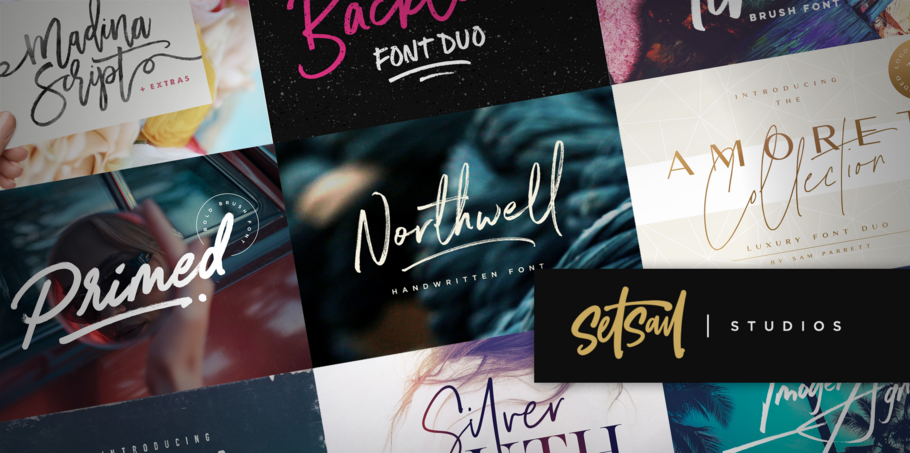
Set Sail Studios.
Set Sail Studios ist eine Einmann-Foundry und wird von Sam Parrett in seinem Home Office in Bristol, Großbritannien, betrieben. Er startete seine Karriere als freiberuflicher Grafik-Designer in der Musikbranche. Irgendwann suchte er sich jedoch eine neue Herausforderung. Er folgte seiner wachsenden Leidenschaft für Schriften und Typografie und brachte 2014 seine erste Schriftart heraus. Dabei war es sein Ziel, die Design-Welt mit einer Palette auffallender, einzigartiger Schriftarten durchzuschütteln, die sich so ganz und gar von den herkömmlichen Buchstabenformen unterschieden. Er hat sich auf handgezeichnete Schrift-Designs spezialisiert. Seine luxuriösen Zeichensätze werden häufig für Lifestyle-Marken verwendet, während seine Pinsel- und Markerschriften oft die perfekte Lösung für Designprojekte im Retrostil oder mit rustikalem Einfluss bieten.
Northwell
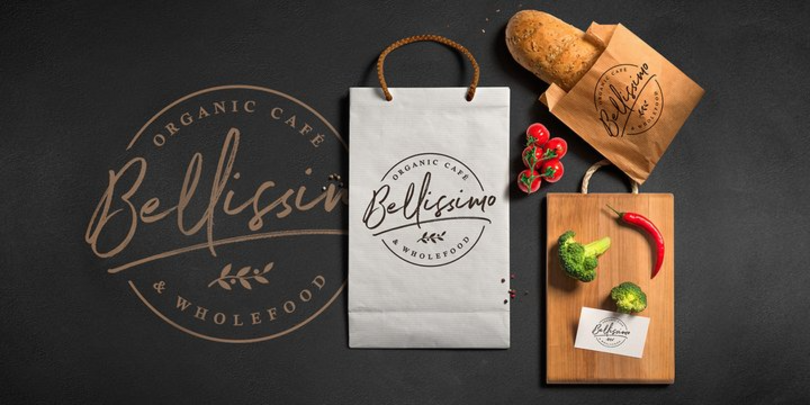
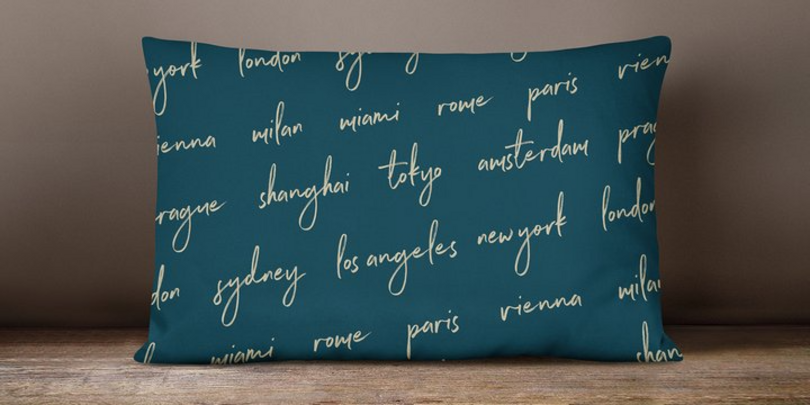
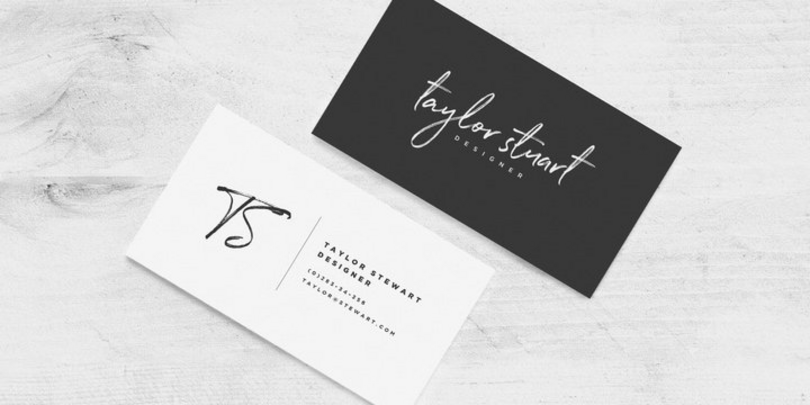
Northwell eine rustikale, elegante handschriftliche anmutende Schriftart mit einem persönlichen Charme, ist mit seinen schnellen trockenen Strichen und seinem Signaturstil eine ideale Lösung für Branding-Projekte, Homeware-Designs oder Produktverpackungen. Die Northwell-Schriftfamilie umfasst eine rustikale, texturierte Version und einen sauberen, polierten Stil. Die saubere Version weist keine raue Pinseltextur auf. Diese wird durch vollständig glatte Ränder ersetzt, die sich optimal für Spezialdrucke eignen oder einfach dem Design einen eleganten Touch verleihen. Viele Consumer-Marken haben Northwell bereits für ihre Marketing-Materialien verwendet, unter anderem Ralph Lauren und die Londoner Café-Kette EL&N. Northwell liefert einen eleganten aber trotzdem persönlichen Touch für die gesamte Marke eines Unternehmens. Sie ergänzt den Stil einer Marke überall dort, wo sie erscheint.
Primed
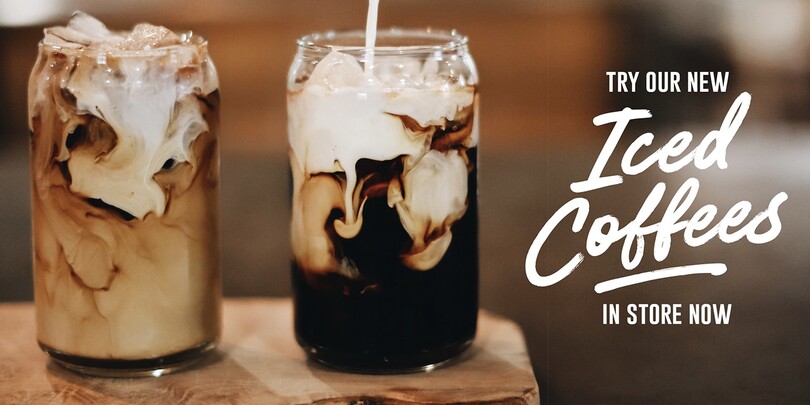
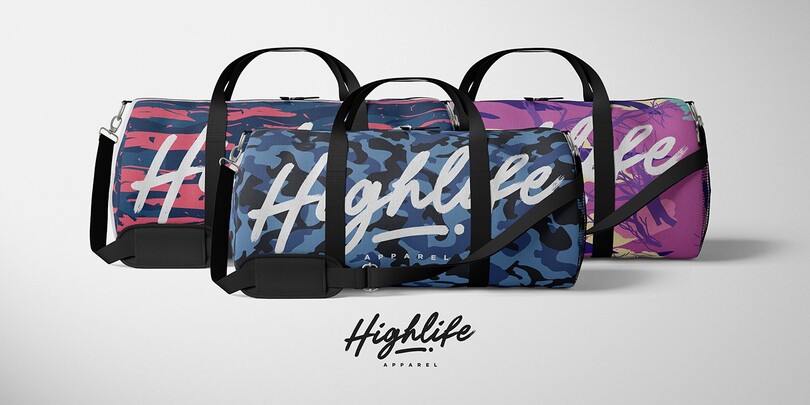
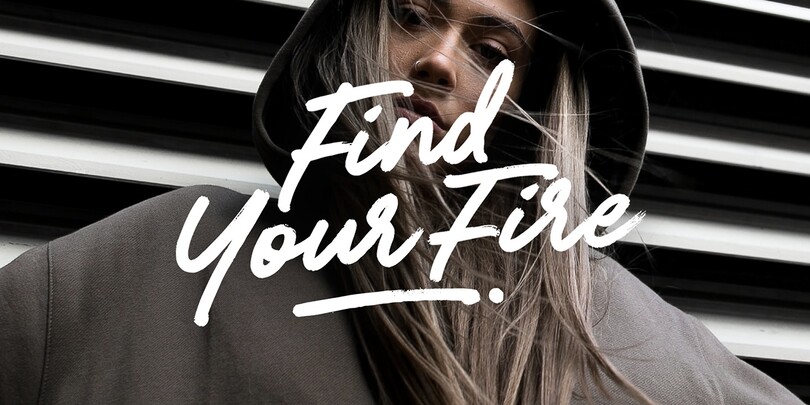
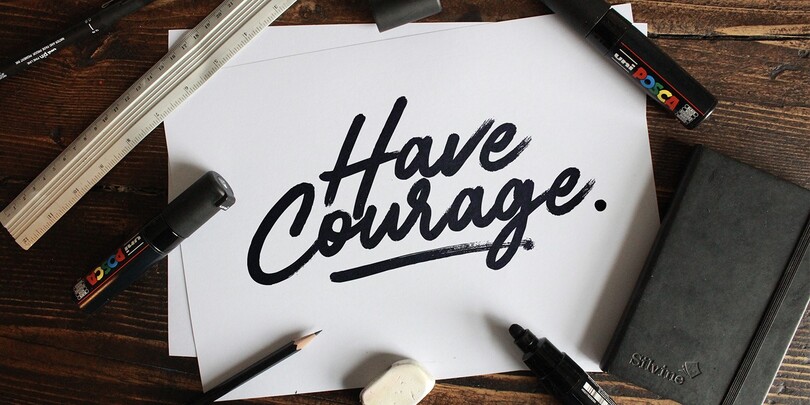
Präsent, plakativ und für den bleibenden Eindruck gedacht. Primed ist eine authentische, handgezeichnete Pinselschriftart, die mit richtigen Markern entwickelt wurde. Perfekt für unübersehbare Display-Texte, Logos, handschriftliche Zitate, Produktverpackungen und vieles mehr! Primed umfasst neben einem vollständigen alternativen Satz Groß- und Kleinbuchstaben auch einen Satz von 18 Schwungbuchstaben, die sich hervorragend für die Untermalung von Buchstaben und einen Hauch von zusätzlichem individuellem Stil eignen. Die alternativen Buchstaben und die Schwungbuchstaben sind als eigenständige Schriftarten enthalten. Primed umfasst außerdem 47 Ligaturen. Diese Doppel- und Dreifachbuchstabenkombinationen tragen zu einem natürlicheren Verbindungs- und Flusseffekt bei.
Silver South
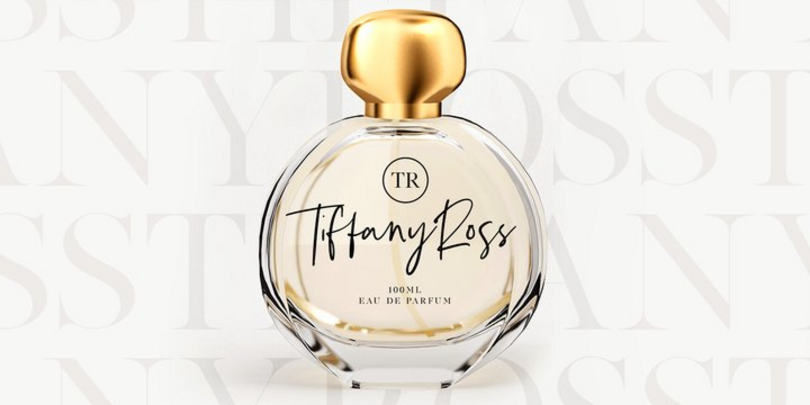
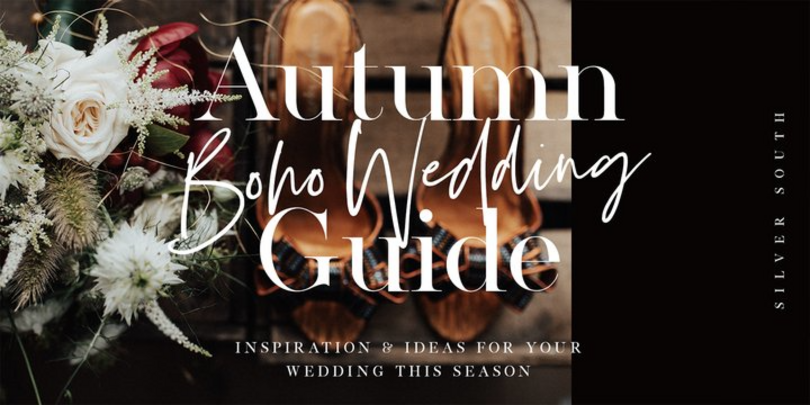
Die Silver South Font Duo ist eine klassische moderne Paarung aus Script- und Serif-Schriftarten. Hier wurden eine elegante Didot-Serif-Schriftart und eine frei fließende expressive Schriftvariante kombiniert, um eine wunderschöne typografische Harmonie für eine große Vielfalt an Design-Projekten zu erzeugen. Dazu gehören Logos und Branding, Lifestyle-Marken, Social Media-Beiträge, Werbeanzeigen und Produkt-Designs. Die Silver South Script umfasst auch 38 Zeichenligaturen und ermöglicht damit einen natürlicheren, stärker handschriftlich geprägten Textcharakter.
Faith and Glory
Faith and Glory: zwei handgezeichnete Pinselschriftarten die perfekt aufeinander abgestimmt sind, um eine wunderschöne, rustikale Typografie mit einem persönlichen Touch zu schaffen. Das Duo eignet sich hervorragend für Logos, gedruckte Zitate, Einladungen, Bild-Overlays, Grußkarten, Produktverpackungen, Textüberschriften usw. Faith and Glory One ist eine Schriftart mit Groß- und Kleinbuchstaben, Satzzeichen, Zahlen, verschiedenen Kleinbuchstabenalternativen und mehrsprachiger Unterstützung. Faith and Glory Two ist eine komprimierte Pinselschriftart, die ausschließlich aus Großbuchstaben besteht. Außerdem umfasst sie Satzzeichen, Zahlen, Alternativen für Zahlenzeichen und mehrsprachige Unterstützung.
Madina Script
Die Madina Script ist eine lebenslustige, aber gleichzeitig elegante Schriftart voller Energie. Designer können damit im Handumdrehen wunderschöne handschriftlich anmutende Typografien erstellen. Die Madina Script mit ihren stark betonten Kurven und Schleifen lässt jeden Text hervorstechen. Sie eignet sich hervorragend für Logos, gedruckte Zitate, Einladungen, Karten, Produktverpackungen und Überschriften. Die Madina Script umfasst einen vollständigen Satz von Kleinbuchstabenvarianten für mehr Authentizität und eine Bonus-Schmuckschrift für einzigartige und elegante finalisierende Touches für Skripttext. Die Schriftart bietet zwei alternative Stile: eine grobe, texturierte Pinselversion für einen rustikalen, handschriftliche Stil und eine saubere, glatte Version für ein seidenartiges Finish.
Backlash
Mit einer ausgefallenen Schriftart und einer Variante mit Kleinbuchstaben eignet sich dieses leidenschaftliche Paar handgezeichneter Markerschriftarten optimal für die Gestaltung handschriftlicher Zitate, Branding- und Logoprojekte, Merchandising, Social Media-Beiträge und Produktverpackungen. Die Backlash Font Duo beinhaltet Backlash Script, eine handgezeichnete Schriftart mit Klein- und Großbuchstaben. Sie beinhaltet außerdem Backlash Small Caps, eine handgezeichnete Sans-Schriftart mit zwei Sätzen an Großbuchstaben (ausschließlich). Beide enthalten Zahlen und Satzzeichen. Die Schriftart umfasst jedoch zusätzlich Ligaturen (Doppelbuchstaben) für „ll“, „tt“ und „ee“ sowie mehrere Schwungbuchstaben. New Yorks „Queen of Rap“, Cardi B, verwendet Backlash für die Illustrationen zu ihrer aktuellen Single „UP“.
Better Times
Better Times eine handgezeichnete Pinselschriftart, ist kräftig, freifließend und mit zwei Sätzen für alle Buchstaben, Zahlen, eine große Anzahl an Satzzeichen und einen Bonus aus 20 handgezeichneten Schwungbögen einfach anpassbar. Die Schriftart wirkt sowohl in Großbuchstaben als auch in Kleinbuchstaben großartig und bietet vielfältige Gestaltungsoptionen. Better Times eignet sich gut für Werbematerialien, handschriftliche Zitate, Produktverpackungen sowie Merchandising- und Branding-Projekte
Amoret Kollektion
Ein beeindruckendes Paar aus einer Luxusschrift und Sans-Schriftarten. Die Schriftarten der Amoret Kollektion sollen sich mit eleganter Schönheit und modernem Stil kontrastieren und ergänzen. Die Schriftart eignet sich hervorragend für luxuriöse Logos, Branding, Produktverpackungen, Einladungen und Zitate. Die Amoret Sans ist eine klassische, kontrastreiche Sans-Schriftart, die nur aus Großbuchstaben, Zahlen und einer großen Bandbreite an Satzzeichen besteht. Si bildet einen großartigen Kontrast zu den Amoret Script-Schriftarten. Die Amoret Script ist dagegen eine dünne und elegante Schriftart mit übertriebenen Strichen und einem lockeren Schwung. Sie umfasst Groß- und Kleinbuchstaben. Die Amoret Script Alt-Version bietet zusätzliche Gestaltungsoptionen mit einem vollständig neuen Satz an Groß- und Kleinbuchstaben sowie vier Schwungbuchstaben.
Lacuna
Lacuna, die neueste Markerschrift von Set Sail Studio, ist eine frische und ausdrucksstarke Schriftart mit Großbuchstaben. Sie wurde mit einem Marker handgezeichnet, um realistische Texturen beizubehalten. Eine großartige Wahl für trendige Logos im Signaturstil, Merchandising, Poster, Musikkunst und vieles mehr. Lacuna umfasst neben einem vollständigen alternativen Satz Groß- und Kleinbuchstaben auch einen Satz von 26 Schwungbuchstaben, die sich hervorragend für die Untermalung von Lacuna-Buchstaben und einen Hauch von zusätzlichem individuellem Stil eignen.